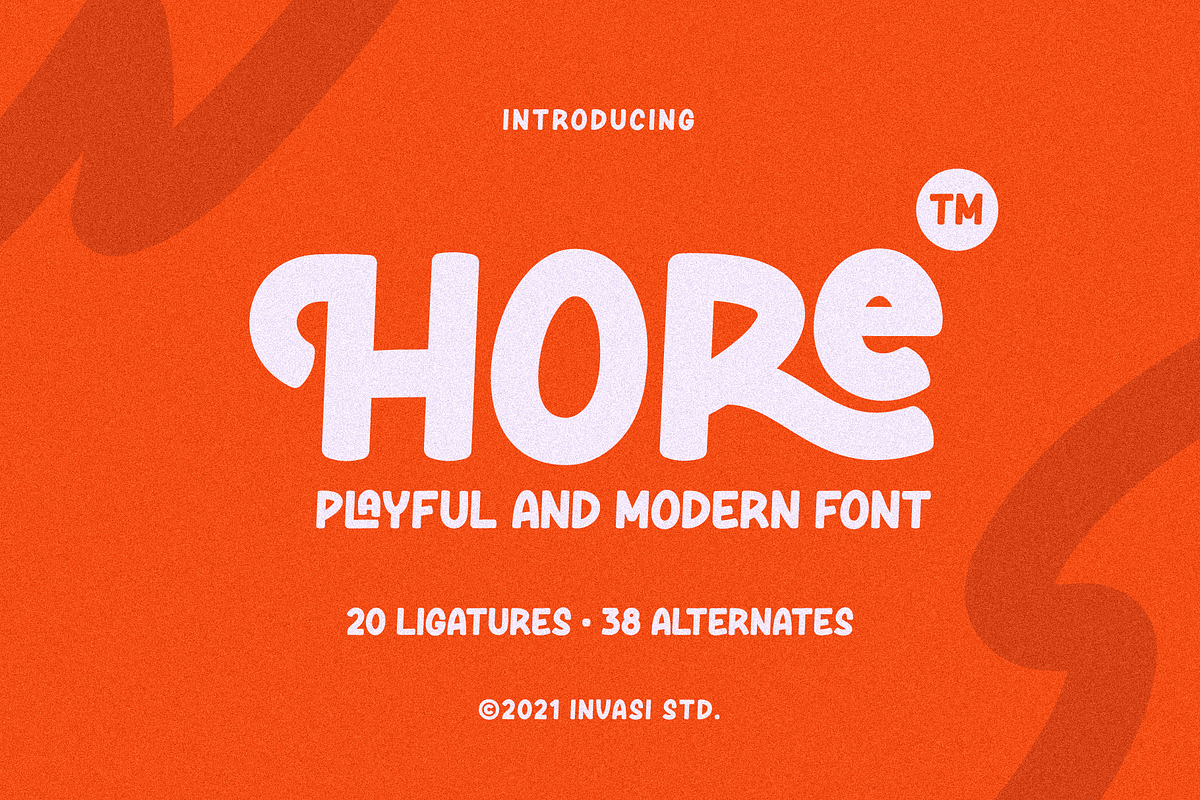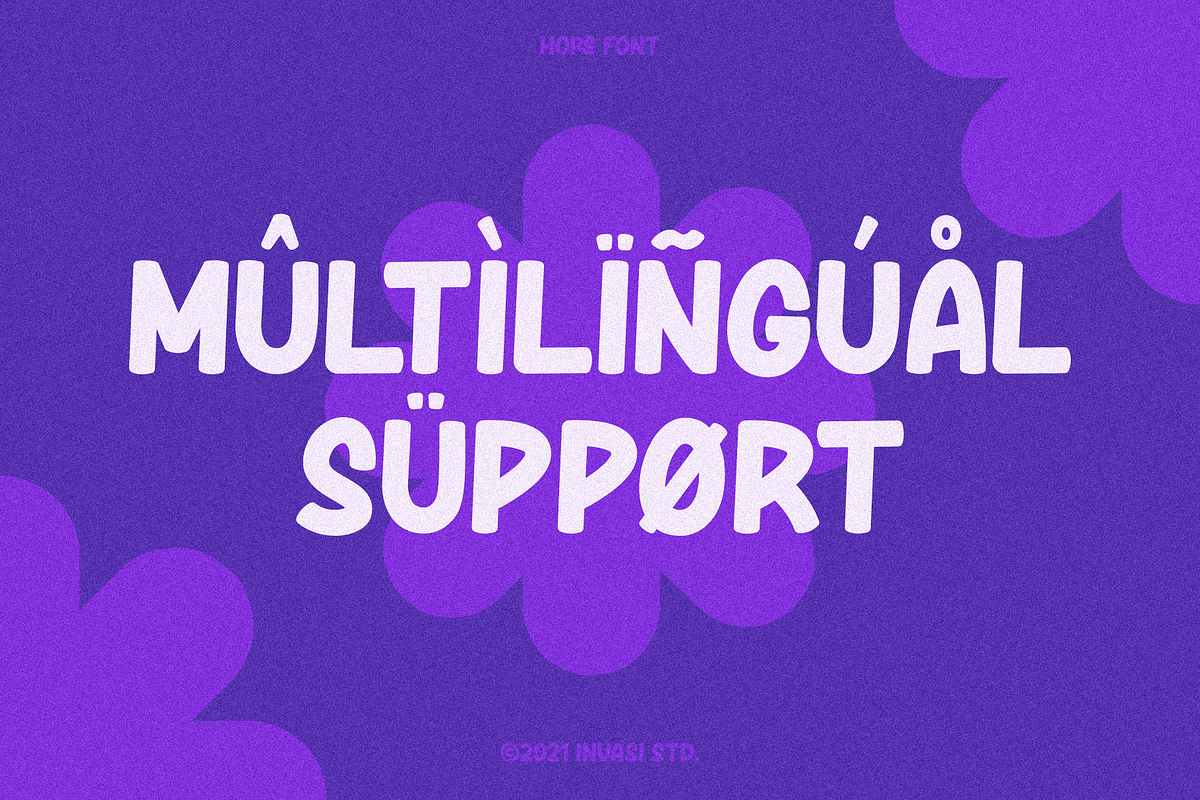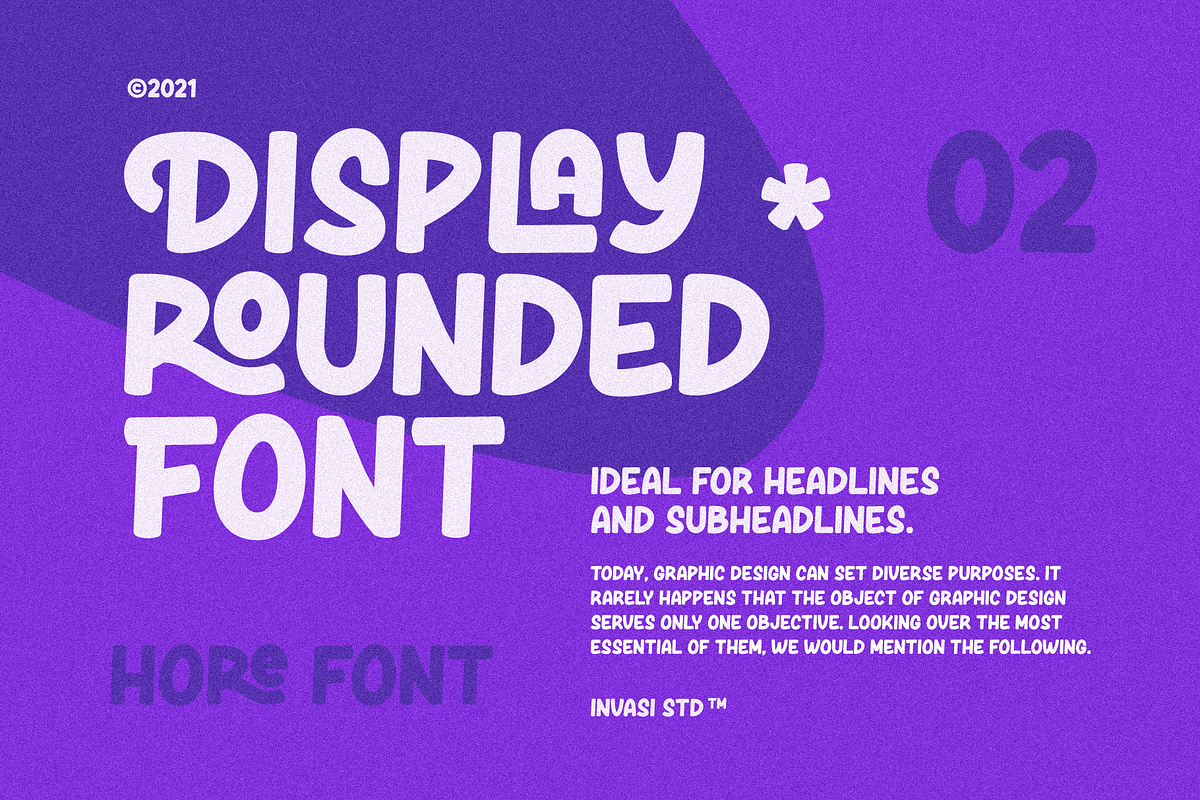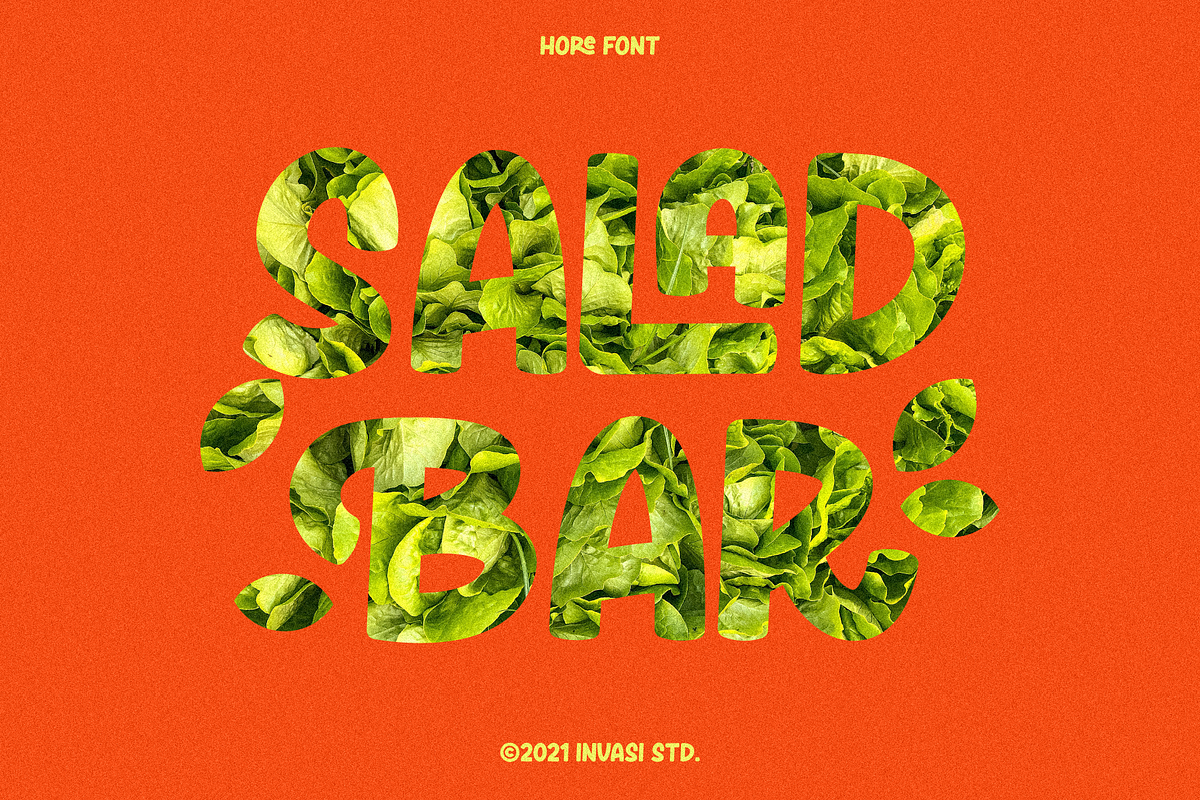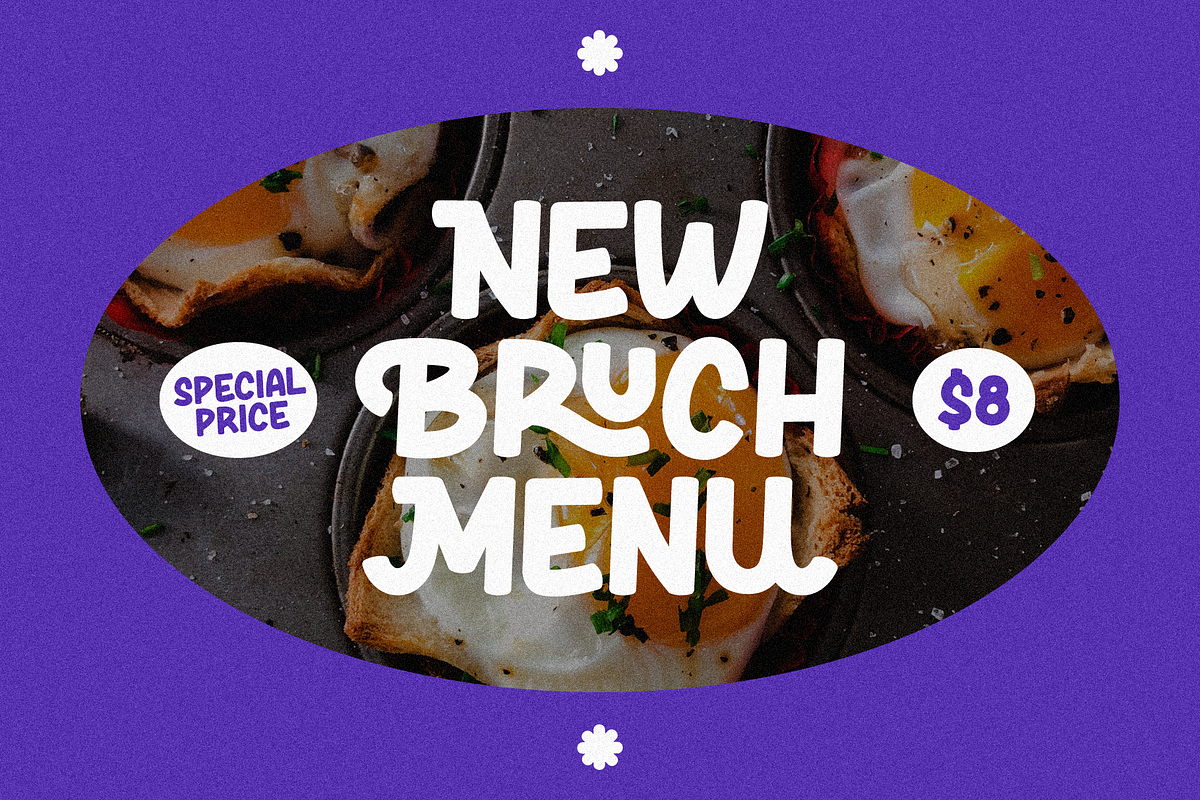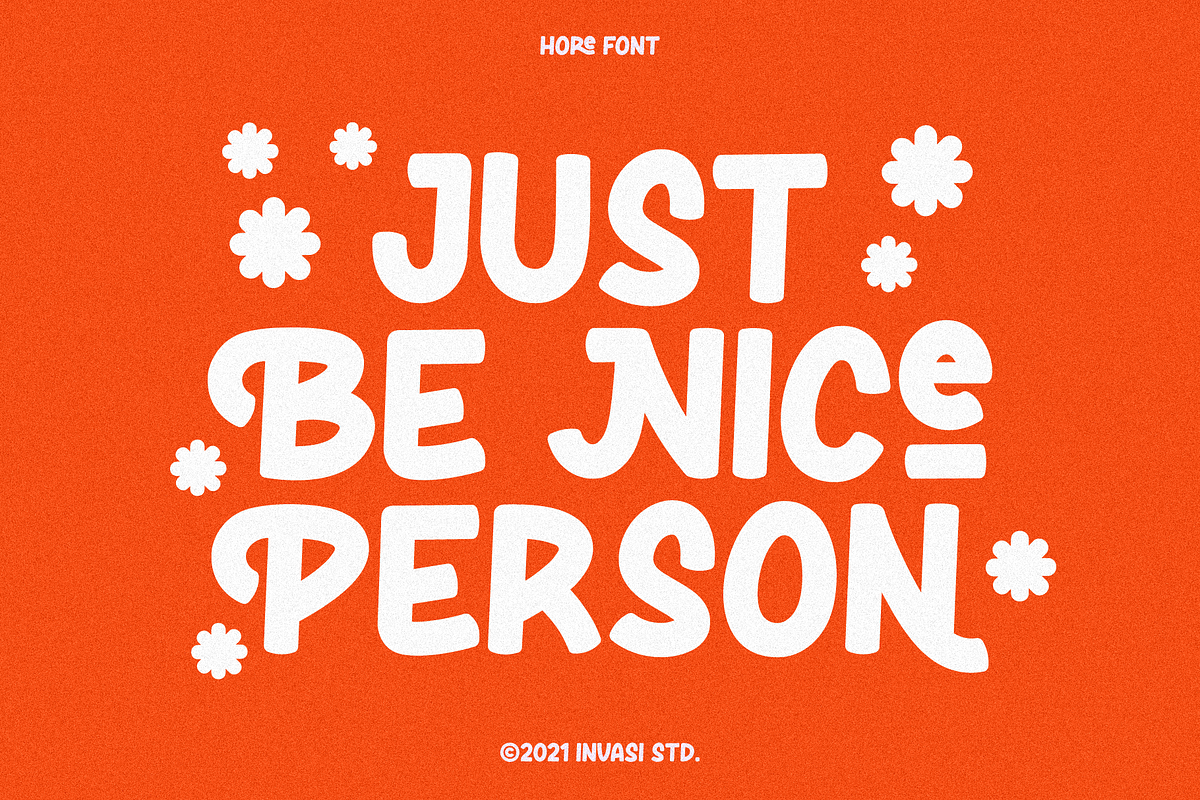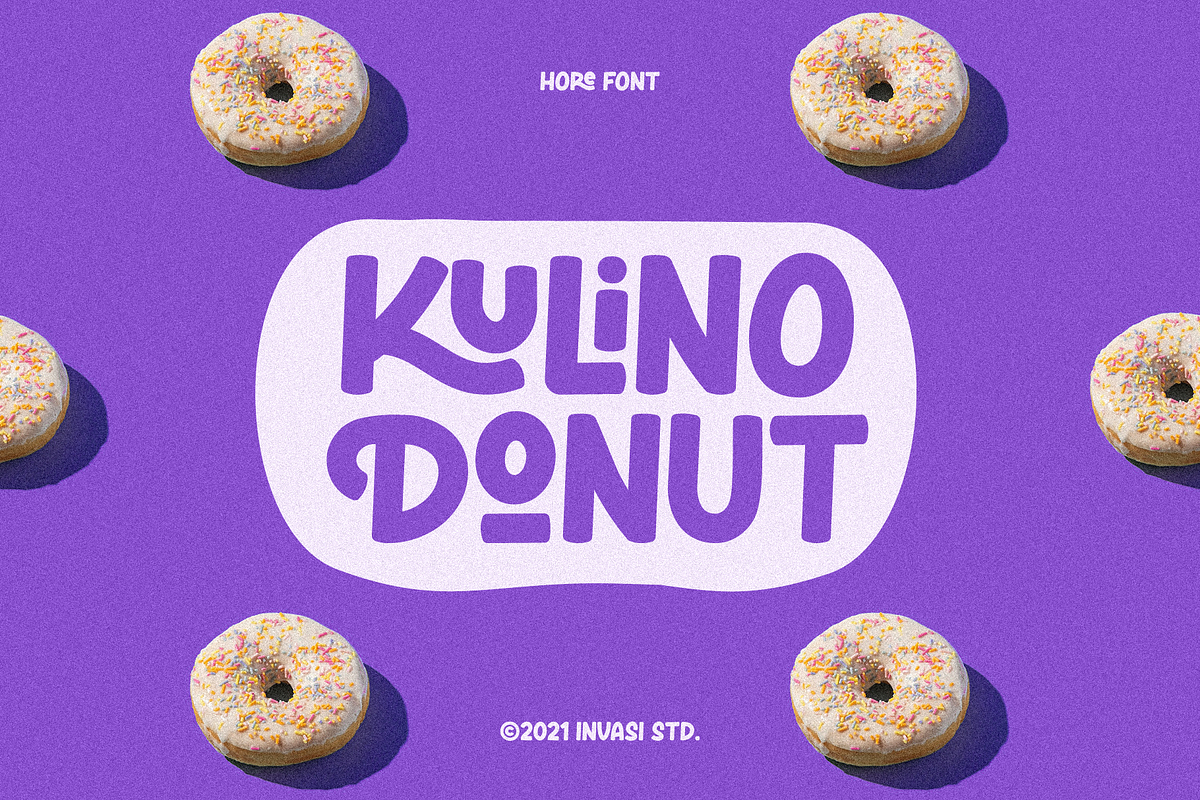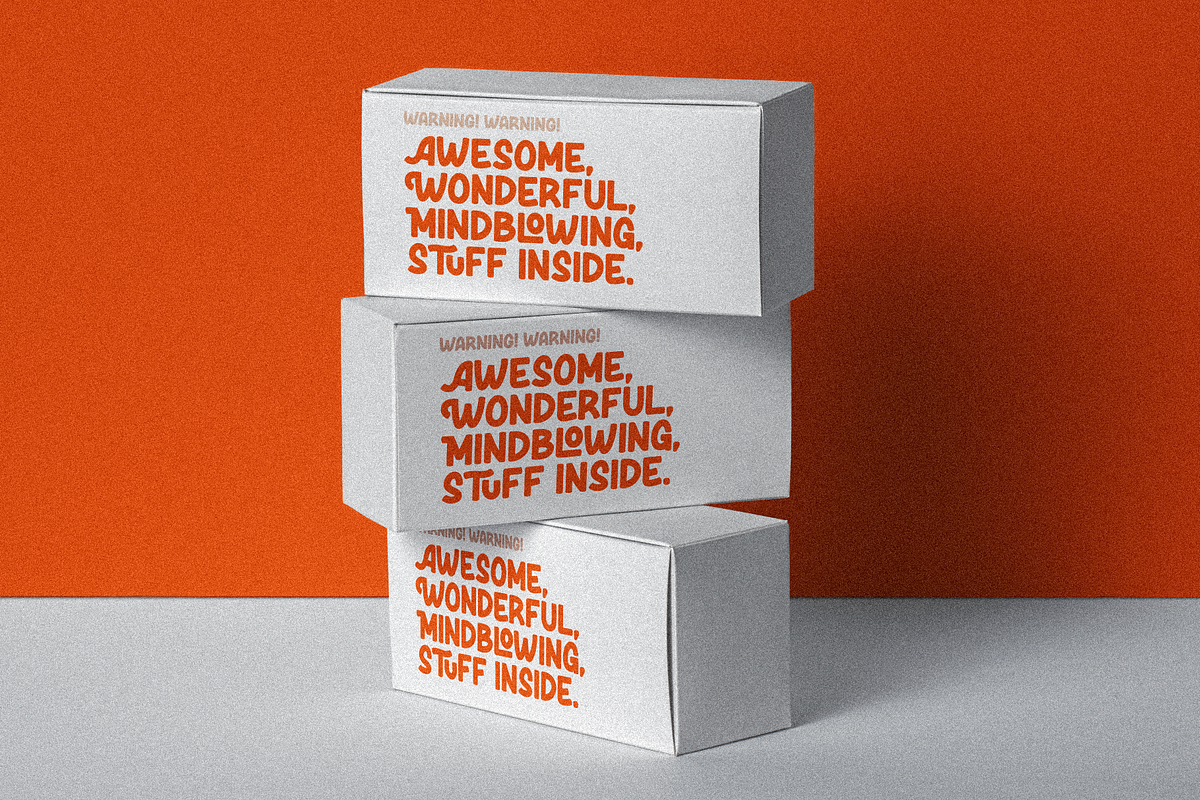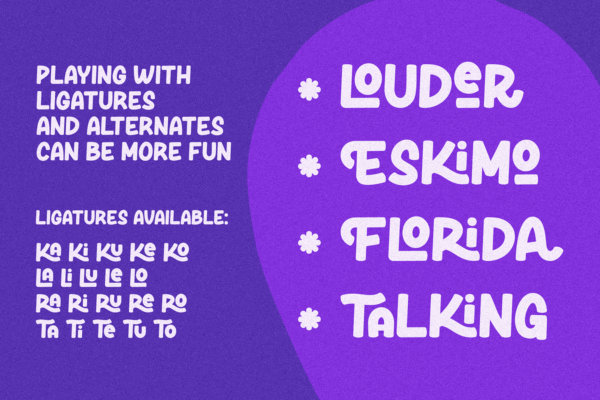
Hore – Playful Font
Hore Font – Koleksi Font Modern, Playful & Profesional
Perkenalkan Hore Font, koleksi font terbaru kami yang menggabungkan nuansa modern, ceria, dan tetap formal dalam satu paket. Dengan banyaknya alternatif karakter dan ligatur menarik, Hore memberikan fleksibilitas maksimal untuk membuat proyek desain Anda lebih hidup dan menyenangkan.
Font ini sangat ideal untuk branding, kemasan produk, logo, poster, atau proyek kreatif lainnya yang membutuhkan sentuhan unik, playful, dan penuh kepribadian.
✨ Fitur Unggulan:
• Dukungan Multibahasa
• Tanda Baca Lengkap
• Alternatif Karakter (Alternates)
• Ligatur Kustom untuk tampilan huruf yang lebih dinamis
Tambahkan karakter ceria ke desain Anda dengan Hore Font – cocok untuk berbagai gaya mulai dari profesional hingga playful!